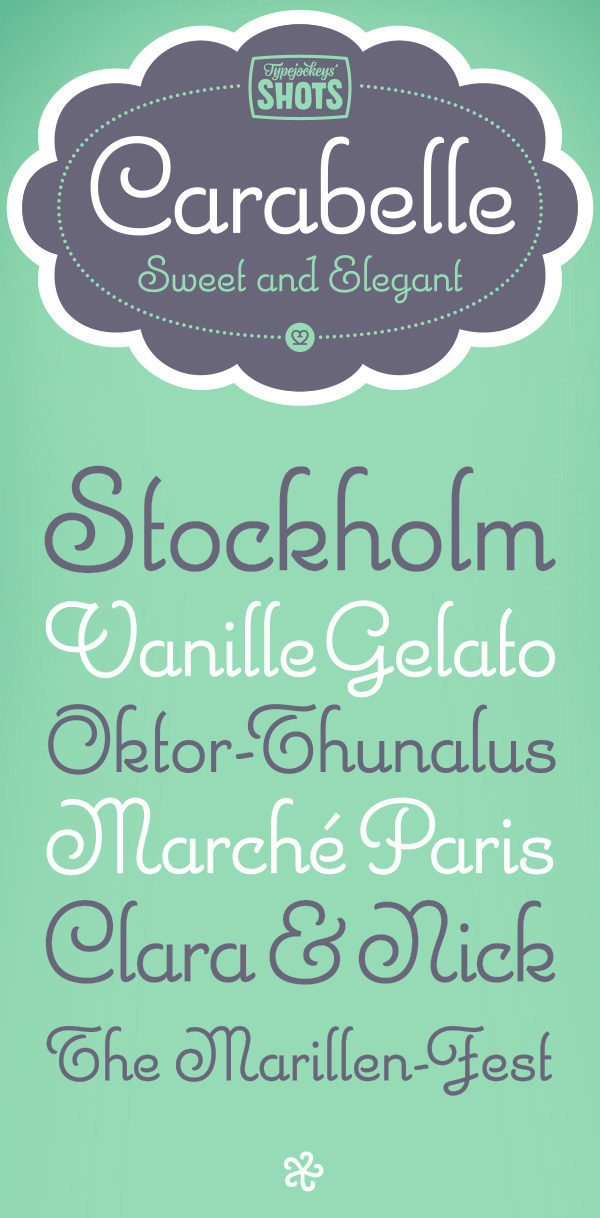
Carabelle und die anderen Neuen von Typejockeys
Schon klar. Ist ja kein Widerspruch. Sonst hätte man es auch schon vor zehn Jahren wieder aus der Schublade kramen können. ;-)
Warum hast du die anderen beiden neuen Fonts nicht genannt?
Um Dir auch noch etwas Spielraum zu lassen. ;-)
Okay … weil ich diese jetzt nicht sonderlich diskussionswürdig fand. Sind für mein Empfinden ja eher Mainstream (trotzdem schöne Comic-Sans-Alternative die Freude).
Mich hatte einfach Eure Meinung zu der Art Schrift wie oben bei der Carabelle interessiert.
Aber weil Du die anderen jetzt schon einmal beigesteuert hast, nenne ich den Strang gern noch um. Aus »Carabelle – die Neue von Typejockeys« wird »Carabelle und die anderen Neuen von Typejockeys«.